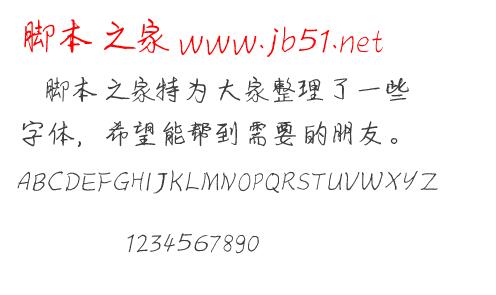
呆萌的豬豬女孩字體(豬豬女孩藝術(shù)中文字體)是一款很優(yōu)秀好用的藝術(shù)個(gè)性中文字體。第一眼看上去就感覺非常的整齊美觀,帶一點(diǎn)點(diǎn)的小潦草,字形結(jié)構(gòu)非常的連貫流暢,藝術(shù)性跟實(shí)用性兼?zhèn)?,可以?yīng)用于廣告海報(bào)印刷等領(lǐng)域,喜歡這款字體的朋友歡迎來下載